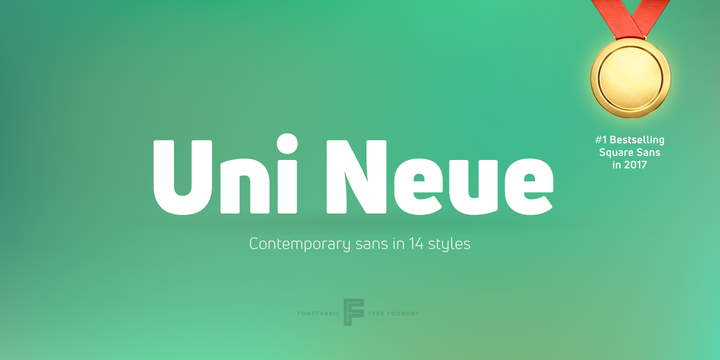
Designed by Svetoslav Simov and Plamen Motev in 2017. Published by Fontfabric.
Он относится к шрифту без засечек и представлен в четырнадцати красивых стилях. Каждый стиль создает разные стили и выглядит фантастически.